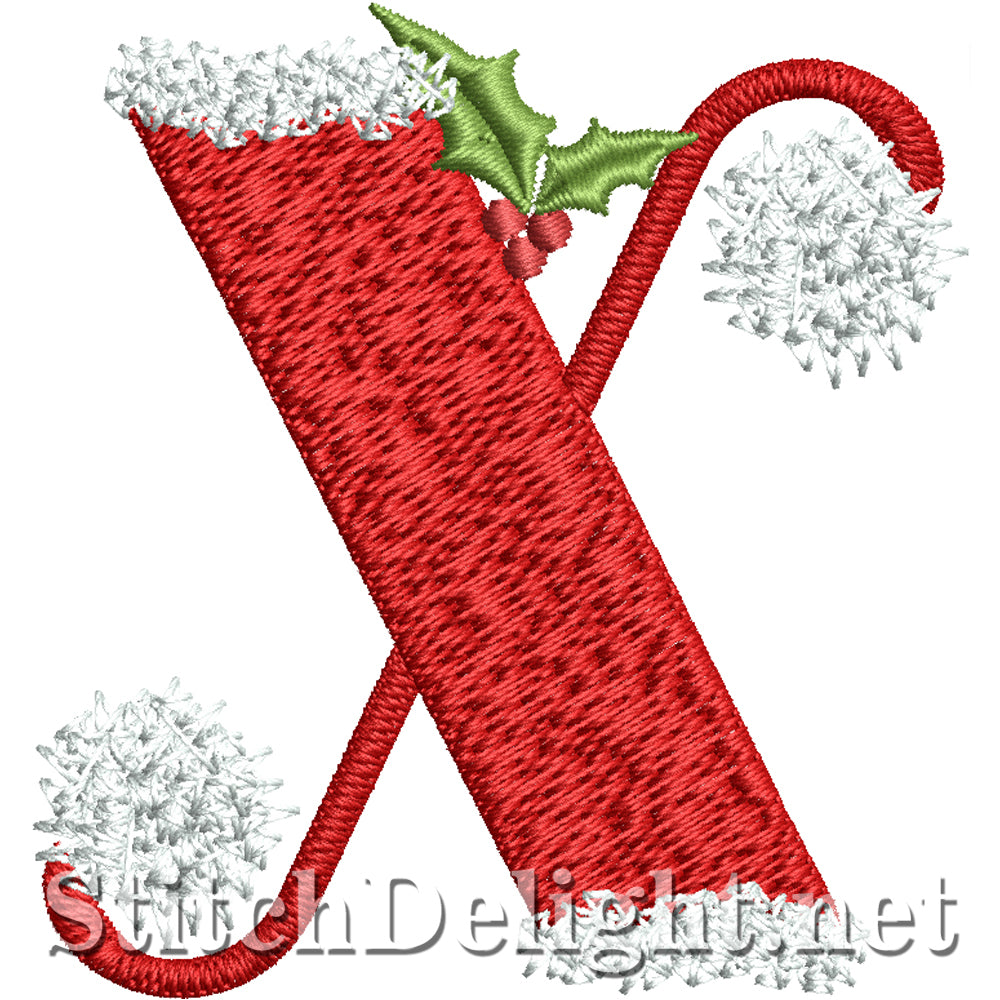
HOE0092 Jolly Festive Police X
Il s'agit d'une seule lettre de la police Jolly Festive. Conçue pour s'adapter au 4x4, cette police adorable a une hauteur moyenne de seulement 2,2 pouces, ce qui la rend parfaite pour broder sur des bas et des cadeaux de Noël.